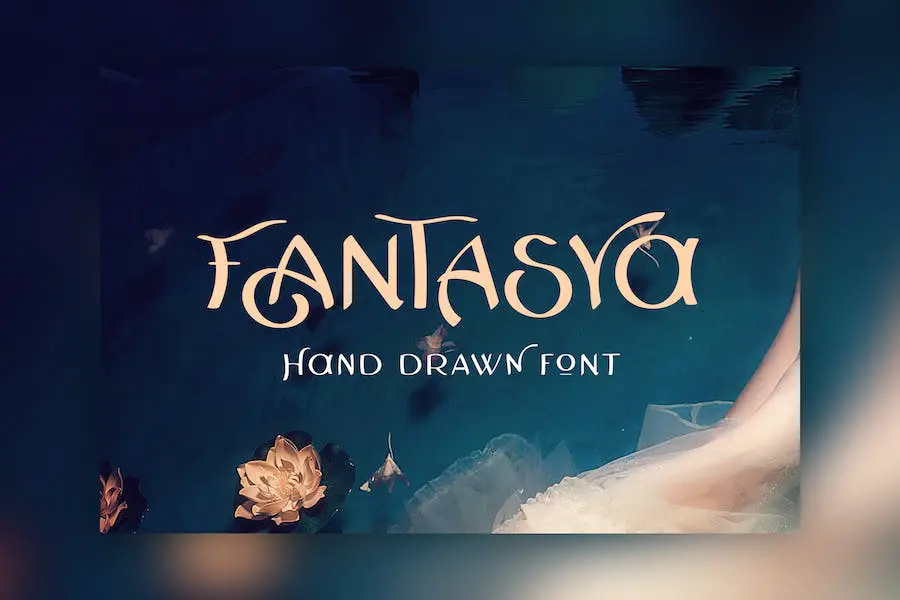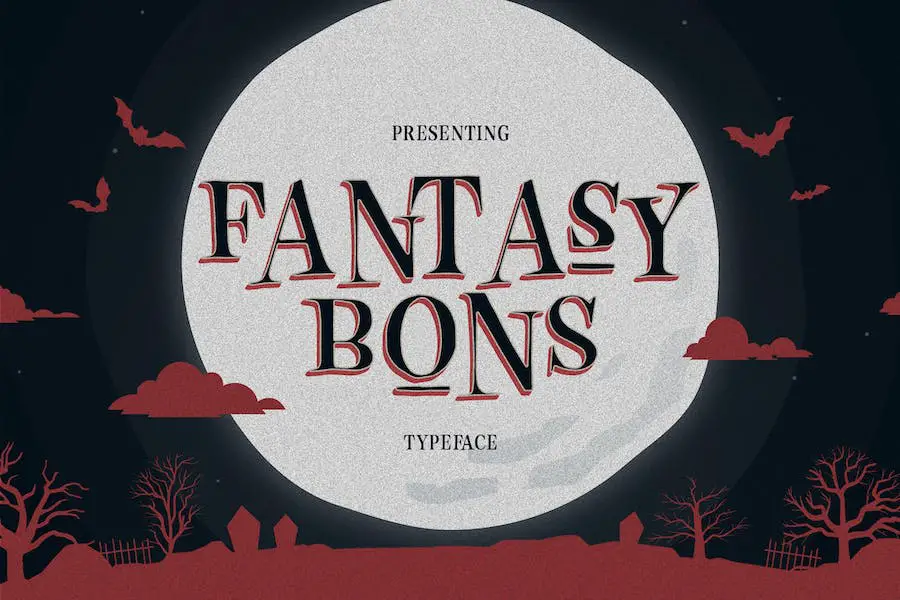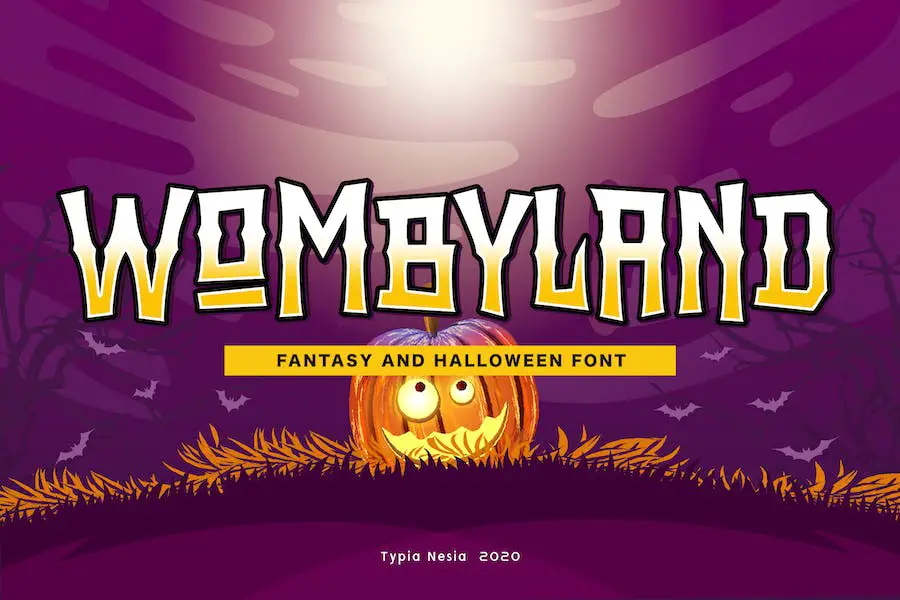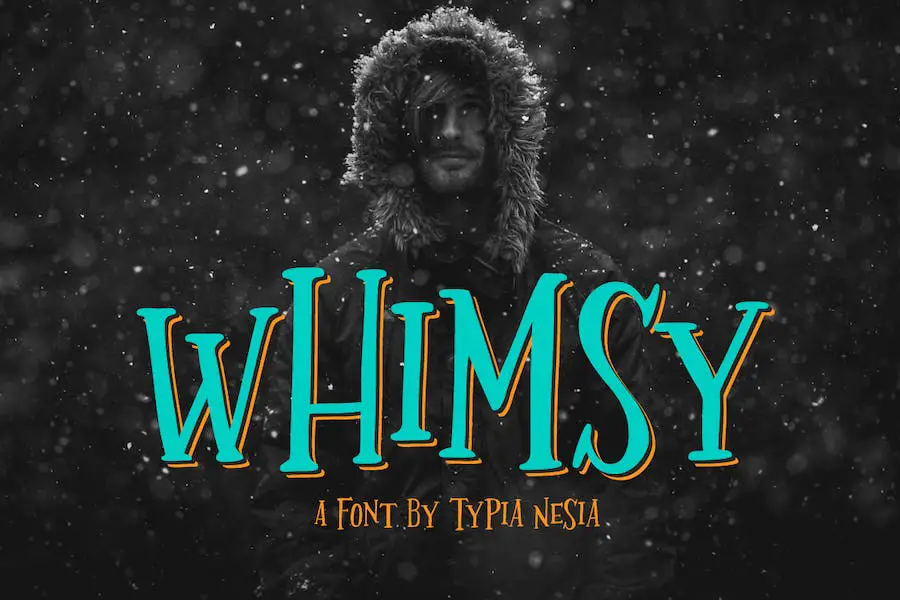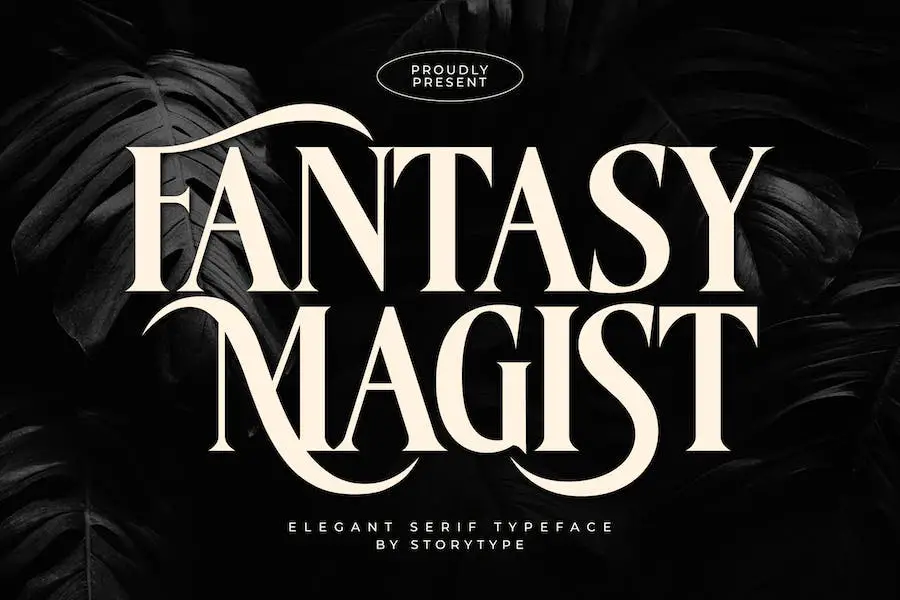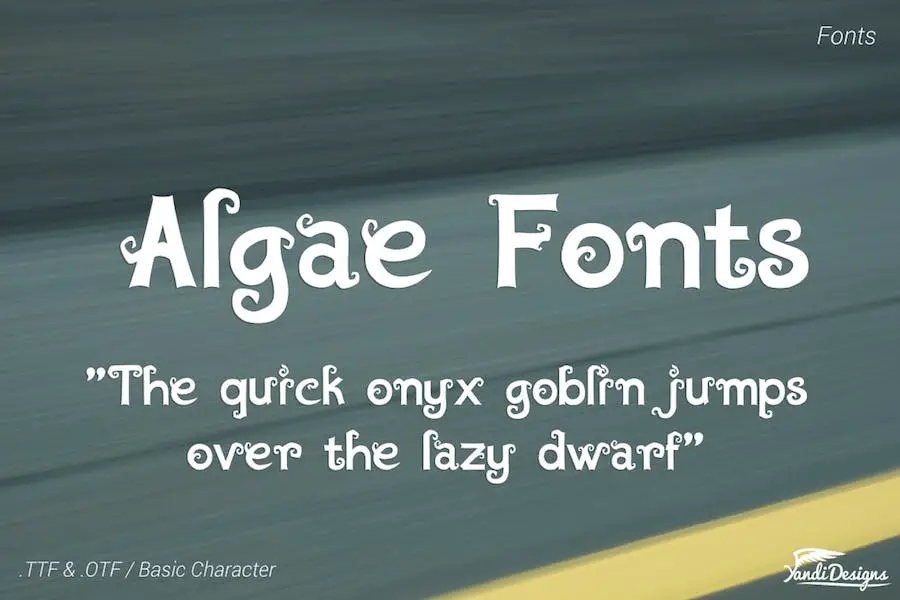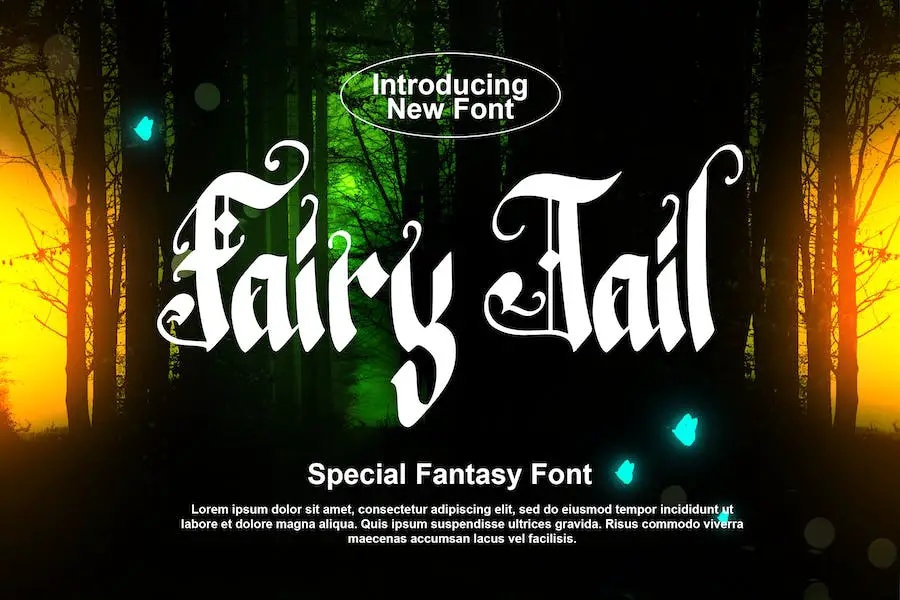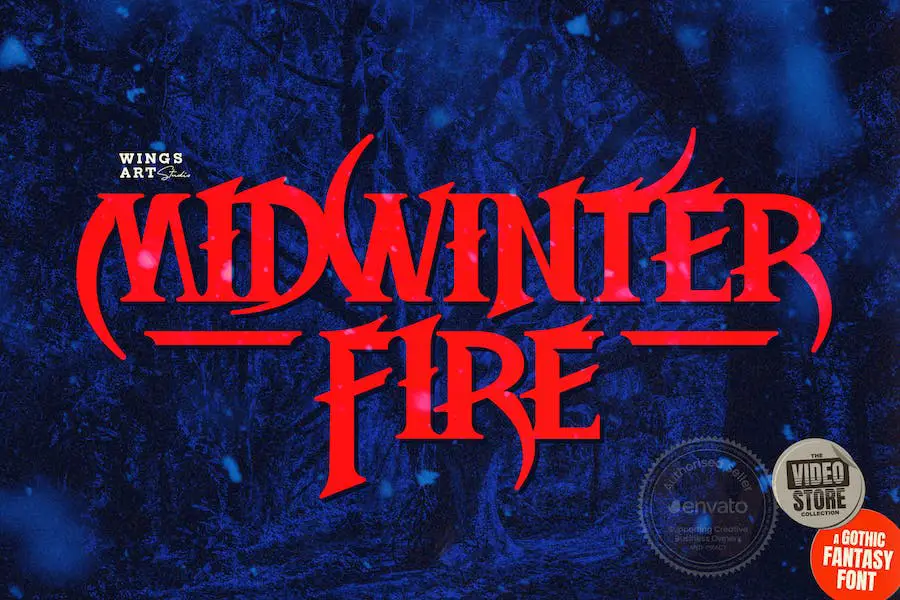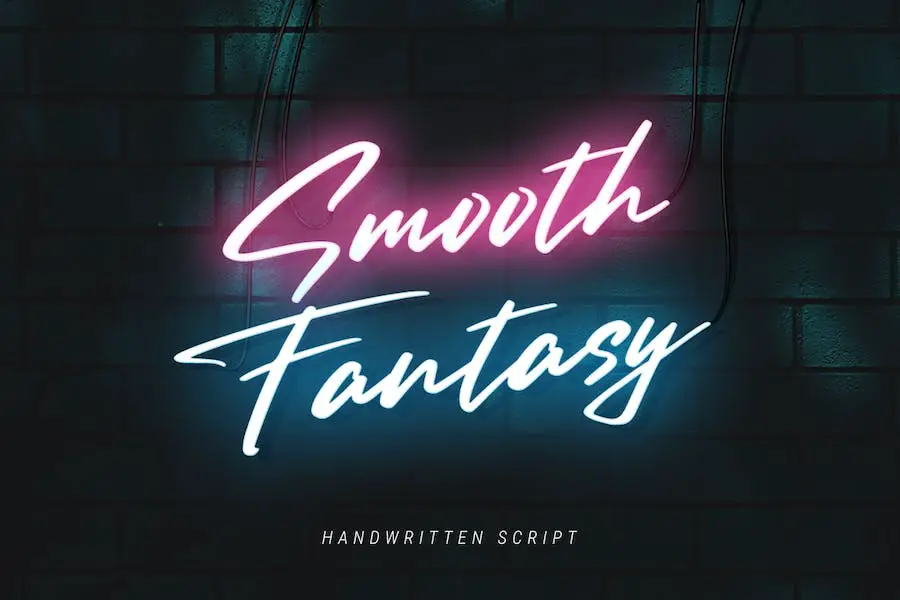
23 meilleures polices fantastiques 2023 (gratuites et premium)
Publié: 2023-08-22Êtes-vous un graphiste à la recherche de la police parfaite pour élever le design de votre projet à un tout nouveau niveau de fantaisie ? Cherchez pas plus loin!
Dans cet article de blog, nous avons compilé une liste des 23 meilleures polices fantastiques qui ne manqueront pas d'enflammer votre créativité et d'apporter une touche de magie à vos créations.
Maintenant, vous vous demandez peut-être : « Pourquoi devrais-je m'embêter avec des polices fantastiques ? Qu'est-ce qui les rend si spéciaux?" Alors, laissez-moi vous dire! Les polices fantastiques sont un moyen fantastique d’ajouter un élément fantaisiste et enchanteur à vos créations.
Que vous travailliez sur la couverture d'un livre de conte de fées, sur un site Web sur le thème fantastique ou même sur une affiche mystique, l'incorporation de la bonne police peut faire toute la différence.
Selon des études récentes, l’utilisation de polices fantastiques dans la conception peut augmenter l’engagement des lecteurs jusqu’à 67 %. Et pas seulement cela, cela contribue également à créer une expérience visuelle mémorable pour votre public, laissant une impression durable.
Donc, si vous cherchez à captiver vos spectateurs et à faire une déclaration avec votre design, ces polices fantastiques sont votre choix de prédilection.
Dans cet article, nous vous guiderons à travers un voyage enchanteur rempli des 23 meilleures polices fantastiques disponibles. Chaque police a été soigneusement sélectionnée et minutieusement vérifiée pour garantir qu'elle répond à nos normes élevées de qualité et de créativité.
Ainsi, que vous travailliez sur un logo mystique, une affiche magique ou une invitation envoûtante, nous avons ce qu'il vous faut. Préparez-vous à donner vie à vos créations avec ces polices fantastiques !
Meilleures polices fantastiques premium
Vous cherchez à ajouter une touche de magie à votre prochain projet de design ? Ne cherchez pas plus loin que notre sélection soigneusement organisée des meilleures polices fantastiques haut de gamme.
Ces polices enchanteresses transporteront vos créations dans un monde d’imagination et d’émerveillement. Explorez les polices uniques et captivantes présentées dans cet article et débloquez un monde de créativité illimitée.
Angle et Fée
Angle & Fairy est une police incroyable qui fera passer vos projets de conception au niveau supérieur. Que vous travailliez sur un logo luxueux, un design éditorial élégant ou un magazine féminin, cette police est parfaite pour ajouter une touche d'élégance et de sophistication.
Il est également idéal pour les marques de cosmétiques, les promotions de mode et les galeries d'art, car il respire le style et la beauté. Avec Angle & Fairy, vous pouvez créer des visuels époustouflants pour des conceptions de papeterie, des mises en page de blogs, des publicités modernes et même des cartes d'invitation.
Cette police est également parfaite pour ajouter une touche artistique à la décoration intérieure ou pour créer des titres captivants pour des romans fantastiques ou des couvertures de jeux. Les possibilités sont vraiment infinies avec Angle & Fairy.
Panikos
Panikos est une police fantastique qui vous transporte dans un royaume mystique de conte de fées. Avec son ambiance magique et légèrement effrayante, cette police serif est parfaite pour créer des designs captivants pour Halloween ou une fête.
Il ajoute une touche enchanteresse à n'importe quel projet, plongeant instantanément votre public dans un monde d'émerveillement et d'intrigue. Examinons plus en détail les attributs qui font de Panikos un incontournable pour les graphistes cherchant à améliorer la conception de leurs projets.
Runes légendaires
Legendary Runes est la police fantastique parfaite pour vous transporter dans un royaume de conte de fées fantaisiste. Avec son esthétique mystique et légèrement audacieuse, cette police est le choix ultime pour créer des designs captivants pour des histoires pour enfants ou pour le développement de jeux.
Que vous travailliez sur une couverture de livre, un dessin de tatouage ou un projet fantastique, Legendary Runes donnera vie à votre vision.
Cette police est non seulement visuellement époustouflante, mais aussi incroyablement polyvalente. Il est compatible avec les logiciels de conception populaires tels que Google, Adobe, Word, Canva, Circuit, Figma, etc. Quelle que soit la plateforme sur laquelle vous préférez travailler, Legendary Runes s'intégrera parfaitement à votre processus créatif.
Argousho
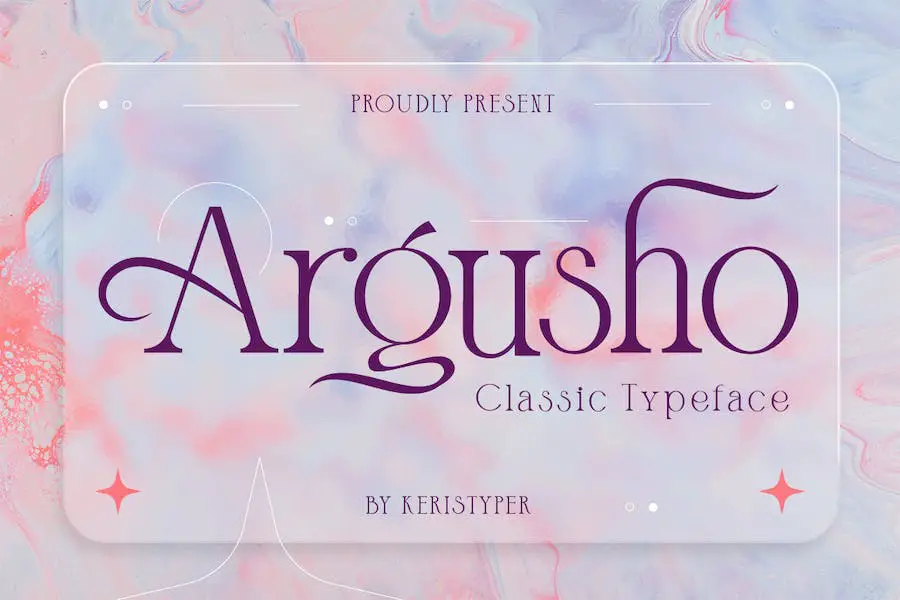
Argusho est une police moderne appelée « It Font » qui apporte une touche d'élégance et de luxe à tout projet. Avec son style classique, il crée une impression sophistiquée qui convient parfaitement à divers besoins de design.
Que vous travailliez sur un logo, des graphiques de réseaux sociaux, des titres de films, des titres de livres ou même de longues lettres de texte, Argusho améliorera votre esthétique visuelle globale. De plus, elle fonctionne parfaitement comme police de texte secondaire aux côtés des options sans ou serif.